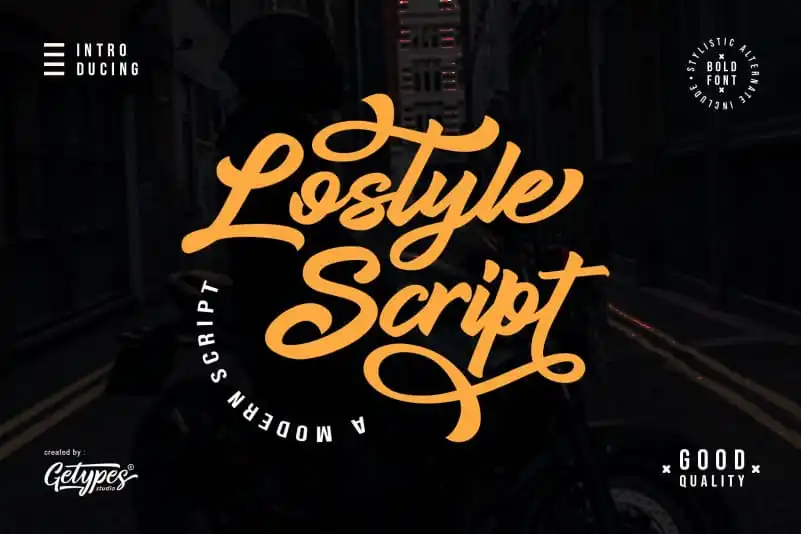
Lostyle Script Font – Download Grátis
A fonte “Lostyle Script Font” é uma nova adição à família das fuentes script que oferece um toque fresco e fluido. Suas linhas são levemente onduladas, refletindo a elegância de uma varinha de pintar em movimento. Esta fonte foi criada por getypes e está disponível para quem busca recursos gráficos versáteis, desde logomarcas até materiais de embalagem e anúncios. Perfeita para designers que desejam trazer um toque único a seus projetos visuais, seja ele para logotipos ou letras decorativas, “Lostyle Script Font” é uma escolha inteligente para qualquer trabalho gráfico. Suas linhas suaves e fluidas são ideais tanto para t-shirts quanto para posters e materiais de embalagem que exigem um toque personalizado.